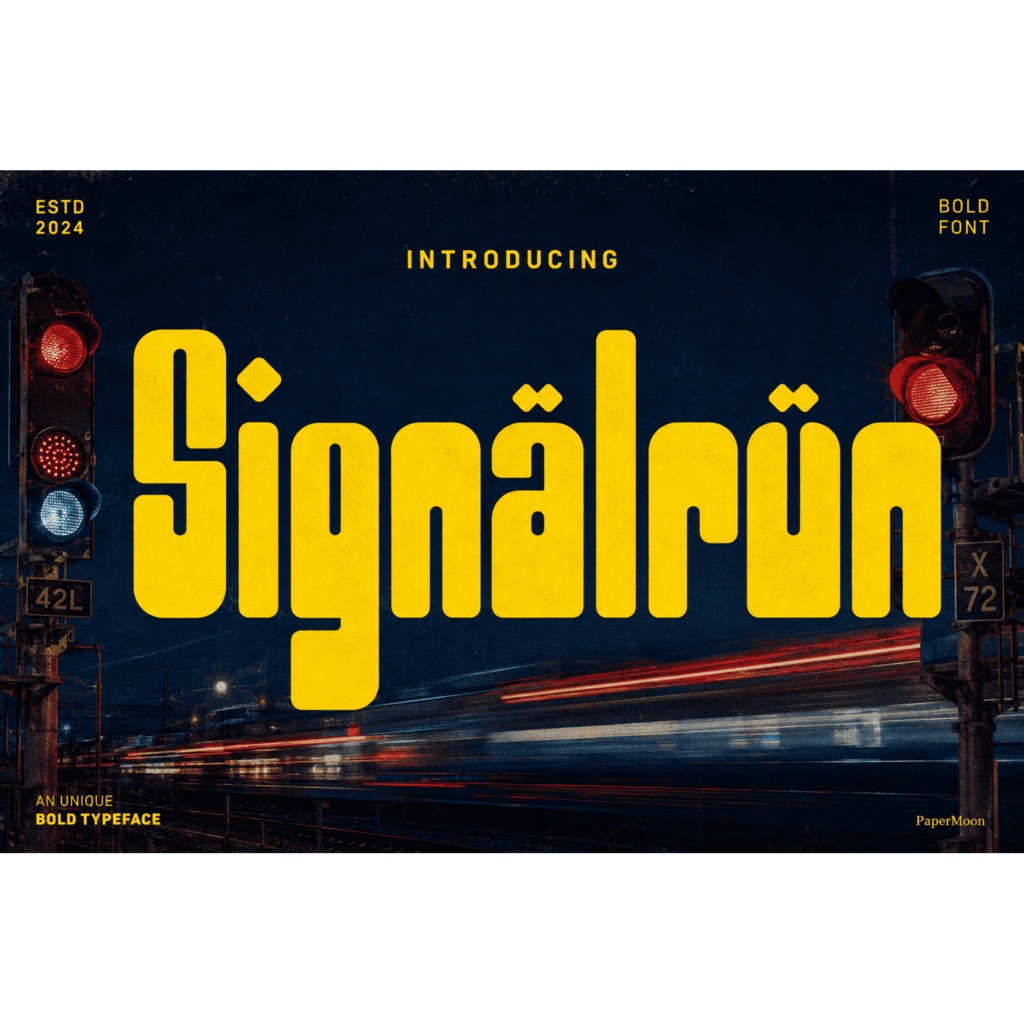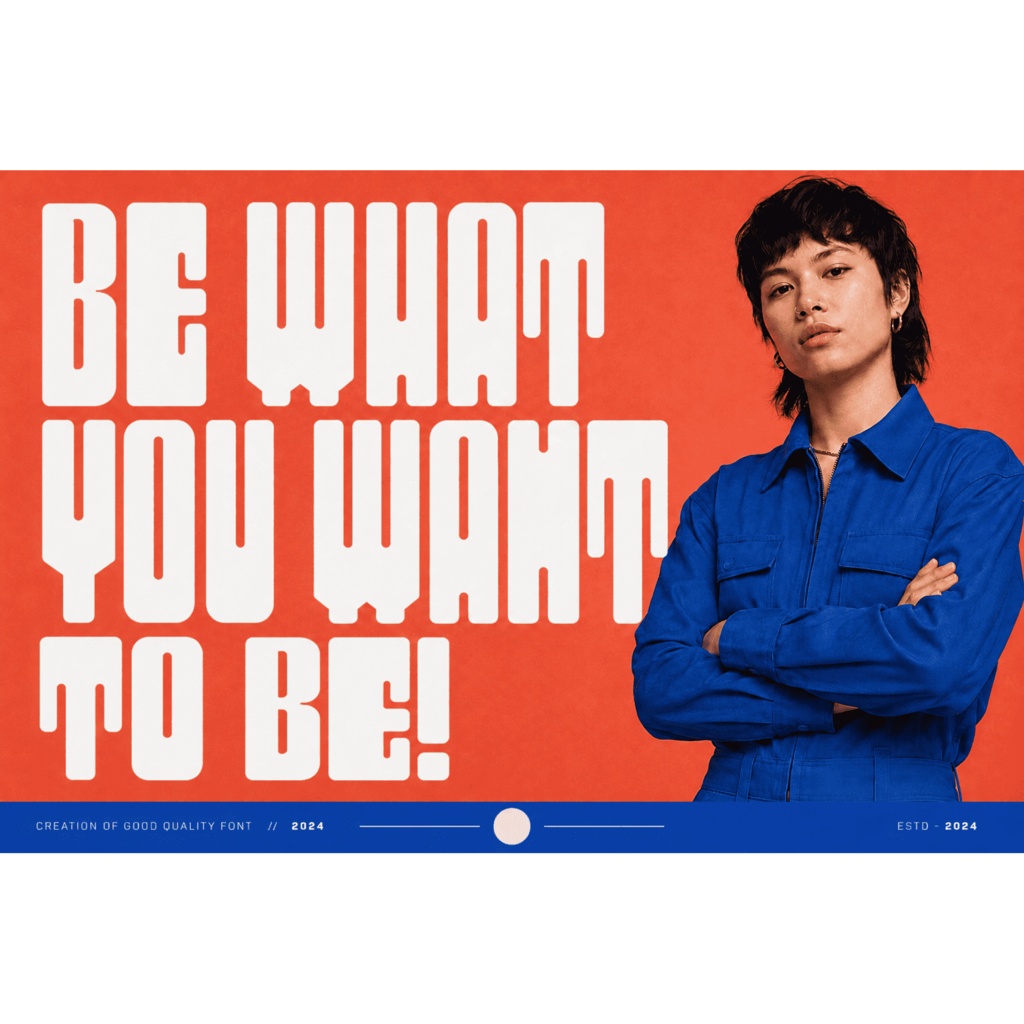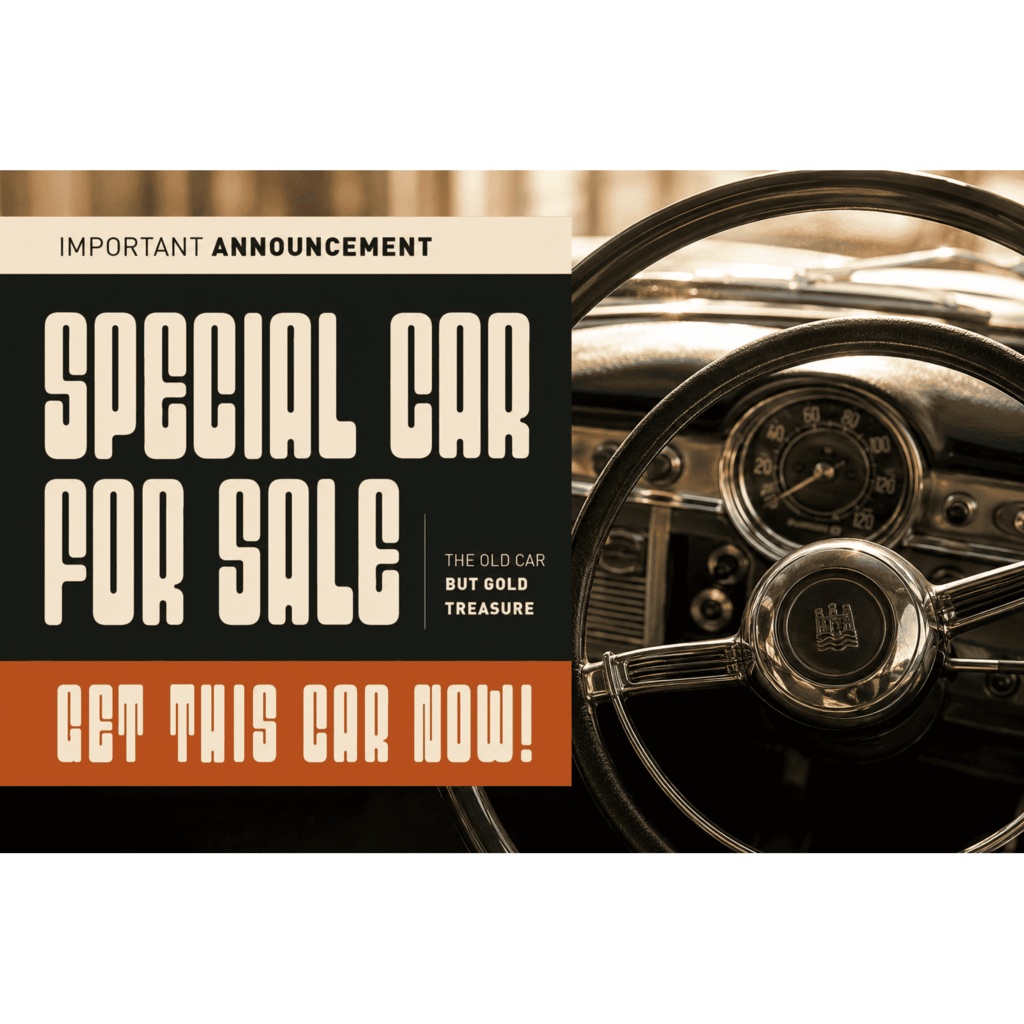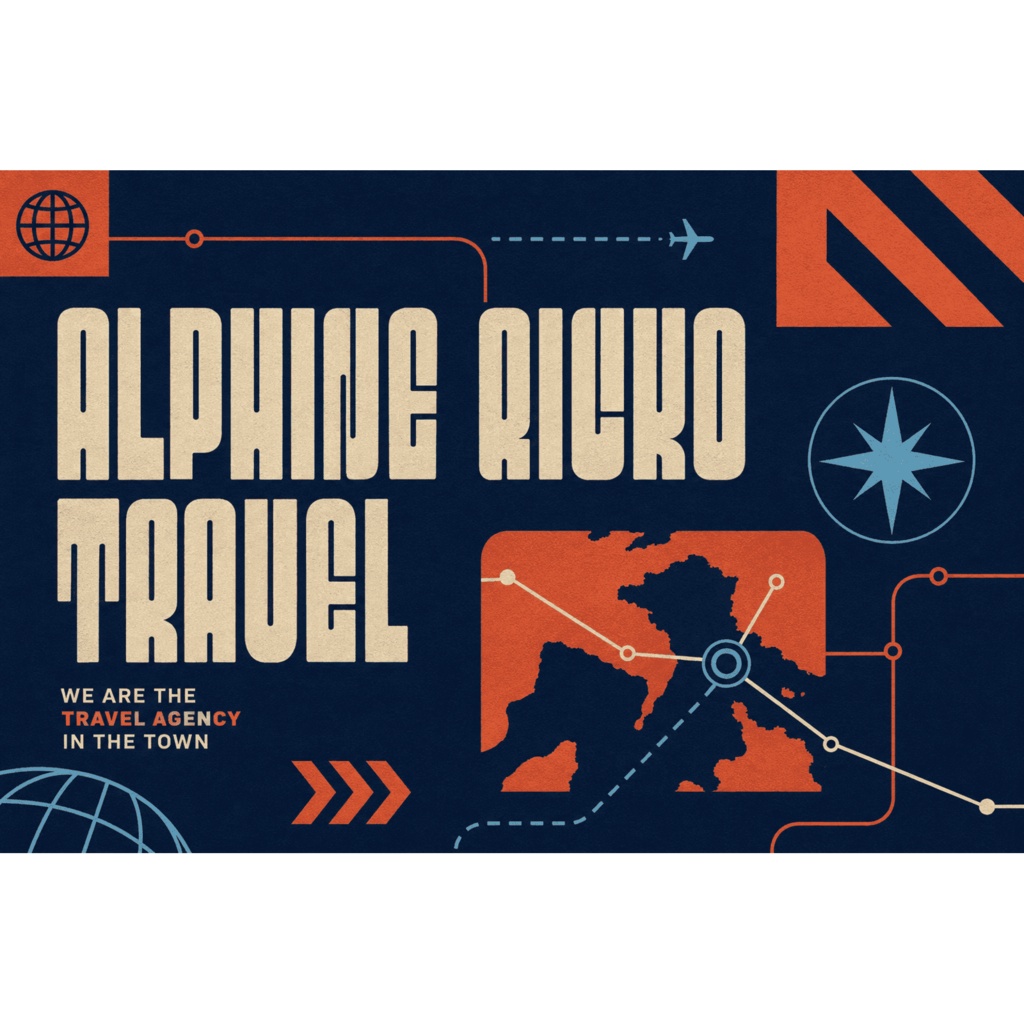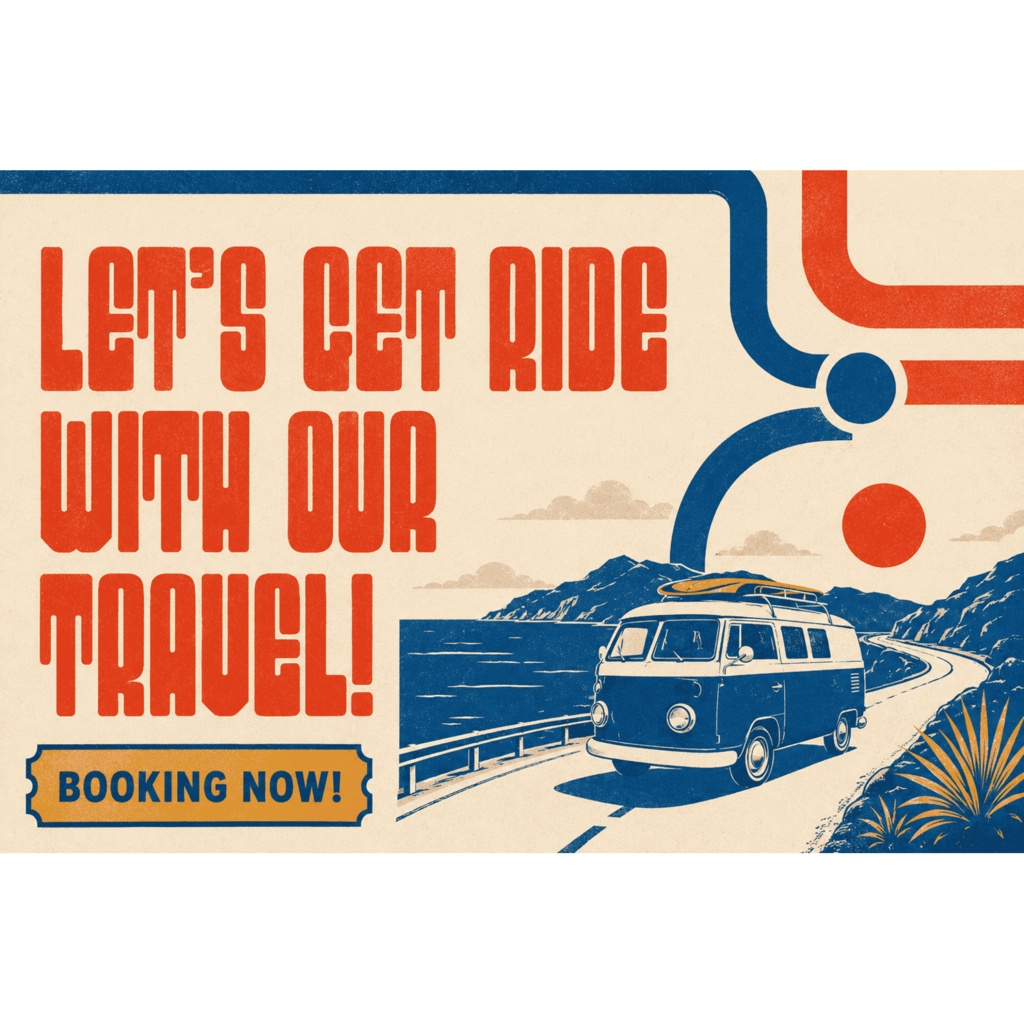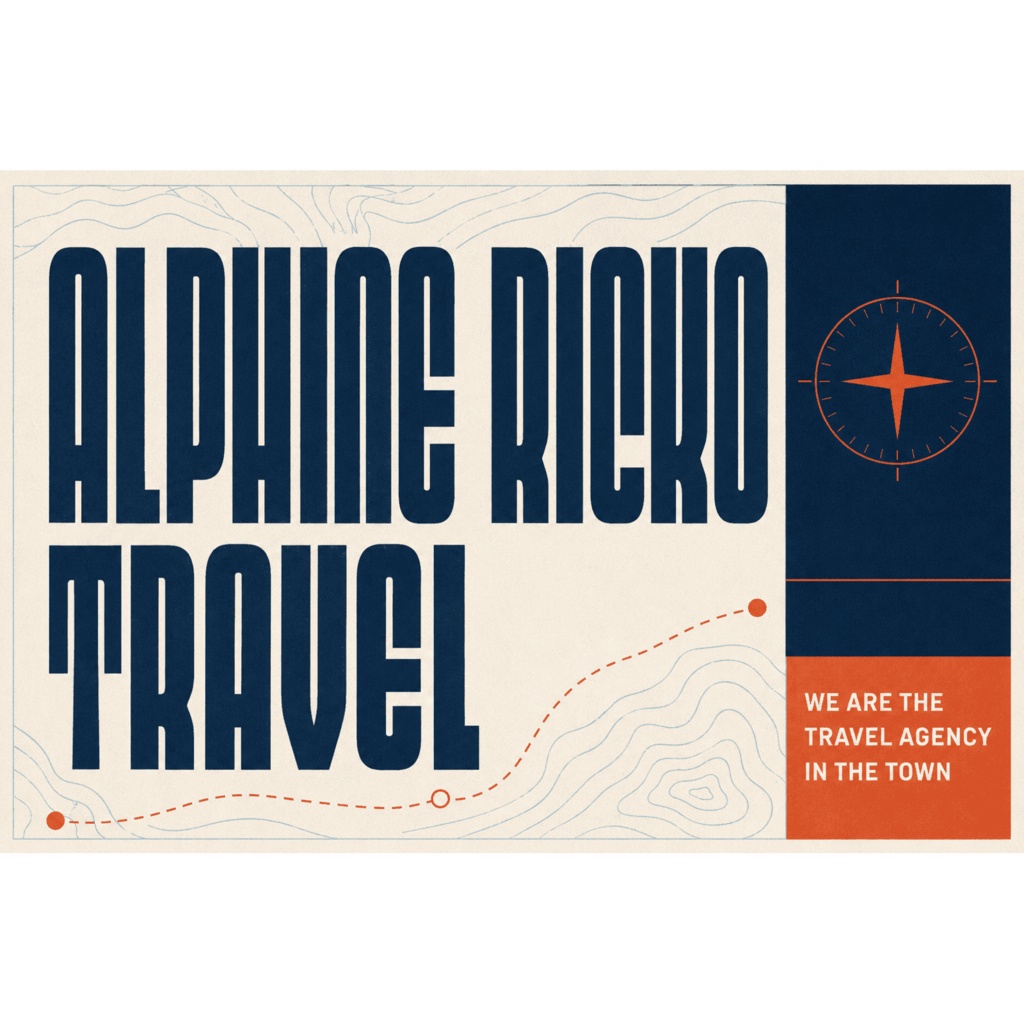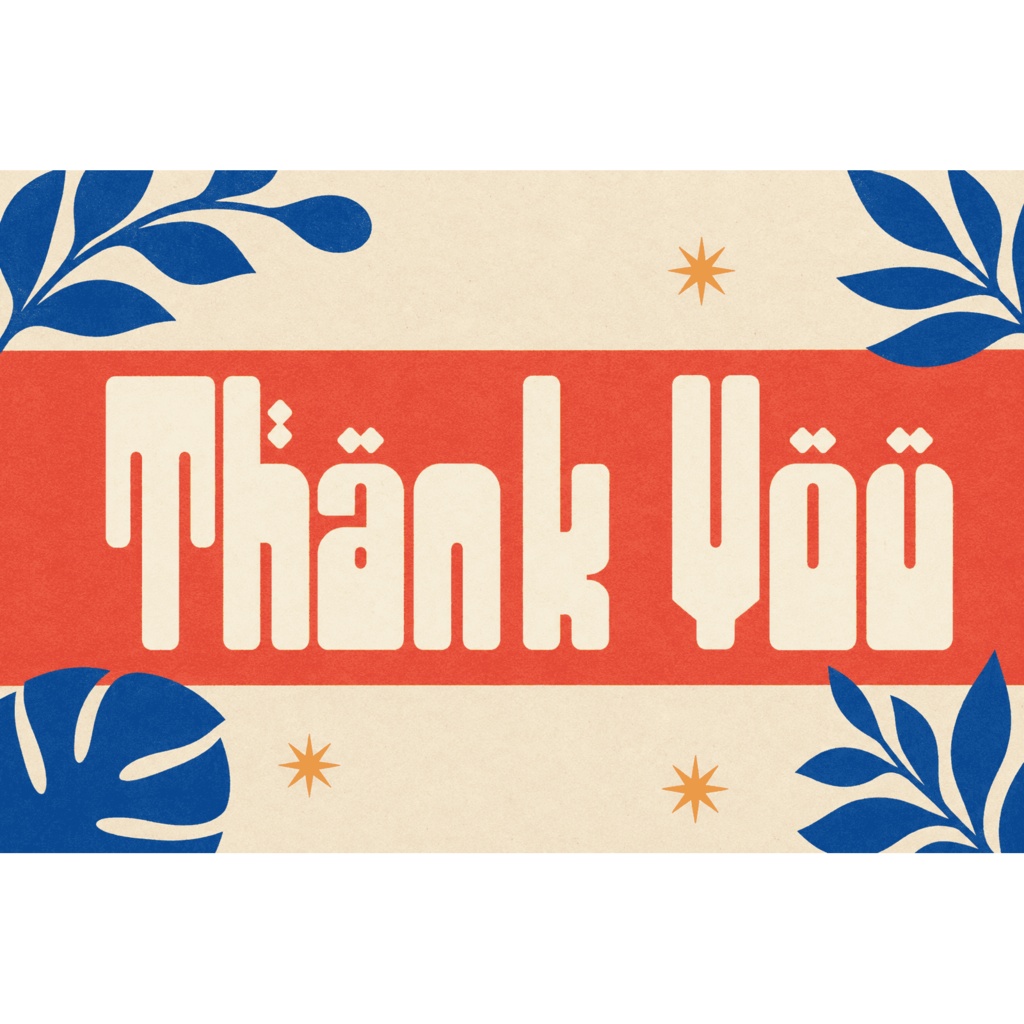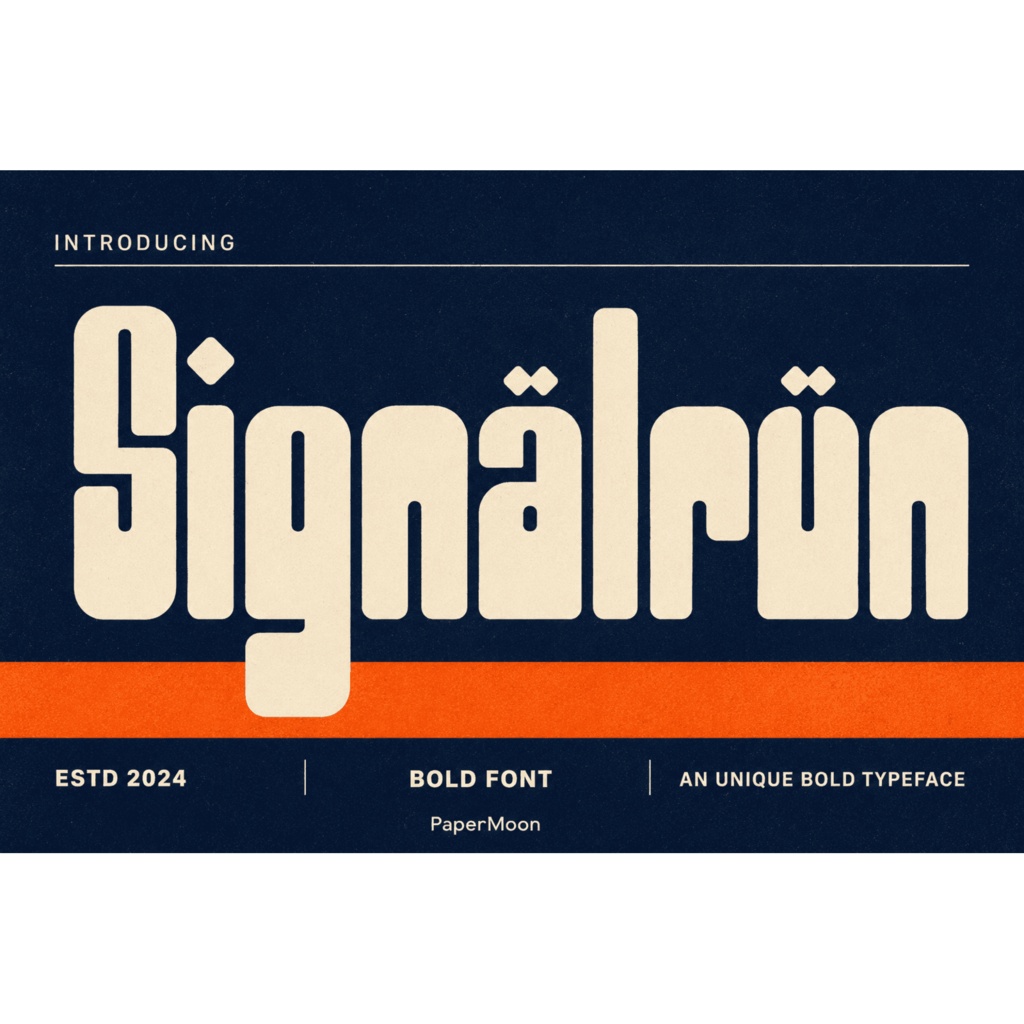
Signalrun | 太字ディスプレイ欧文フォント | ロゴ・見出し・ポスター向け
Signalrun(シグナルラン)は、ロゴ・見出し・ポスター・ブランディングなど、短い文字列で強い印象を残したいデザインに最適な、太字のディスプレイ欧文フォント(display font)です。 ひとつの単語やコンパクトなフレーズが構図全体を引っ張る「主役になる文字」として設計されたシングルウェイト(Signalrun Regular)書体で、力強いストロークと明快なシルエットが、タイトル、ワードマーク、キャンペーンビジュアルにインパクトを与えます。同人誌の表紙、ゲームタイトル、配信サムネイルなど、クリエイター向けのシーンにもよく馴染みます。 収録内容 / Included - Signalrun Regular(シングルウェイト / 1書体) - グリフ数: 237 - 大文字・小文字、数字、記号・約物、ラテン拡張(ダイアクリティカル)文字 - OpenType GSUB(リガチャ・オルタネイト)および GPOS(カーニング / ポジショニング) - 4つの形式: OTF / TTF / WOFF / WOFF2 対応文字 / Character Set - 基本ラテン A-Z / a-z、数字、記号・約物、ラテン拡張文字(アクセント付き文字)を収録しています。 - 日本語(ひらがな・カタカナ・漢字)、キリル文字、ギリシャ文字は収録対象外のラテン系書体です。ラテン系言語のテキスト向けにご利用ください。 用途 / Uses - ロゴ・ワードマーク、ブランドアイデンティティ - 見出し・タイトル、ポスター、パッケージ、グッズ - ゲームタイトル、同人誌・イベントビジュアル、配信グラフィック・サムネイル - Webサイトのヒーロー見出しやデジタルバナーなど、文字を大きく見せるデザイン全般 形式 / Formats - OTF(OpenType Font) - TTF(TrueType Font) - WOFF / WOFF2(Webフォント形式) 対応環境 / Compatibility - OTF・TTF形式をインストールできるPC・Macの一般的なデザイン・DTP・Officeソフトでご利用いただけます。リガチャ・オルタネイト・カーニングなどのOpenType機能の利用可否はアプリケーションに依存します。 - WOFF / WOFF2はWebフォント(@font-face)ワークフロー向けです。 利用許諾 / License - 商用利用にはPaperMoonの商用フォントライセンス(commercial font license)が必要です。 - フォントファイルの再配布・再販・単体での提供はできません。 - 上記以外の詳細な利用範囲(テンプレート化、アプリ・電子書籍への埋め込み、商標登録など)は正式なライセンス文面をご確認のうえ記載してください。公開前にライセンス内容の確認をおすすめします。 購入後 / After purchase - 購入確定後、BOOTHの購入履歴から有償Pro版データ(Signalrun.zip)をダウンロードし、ご利用の環境に合わせた形式をお使いください。